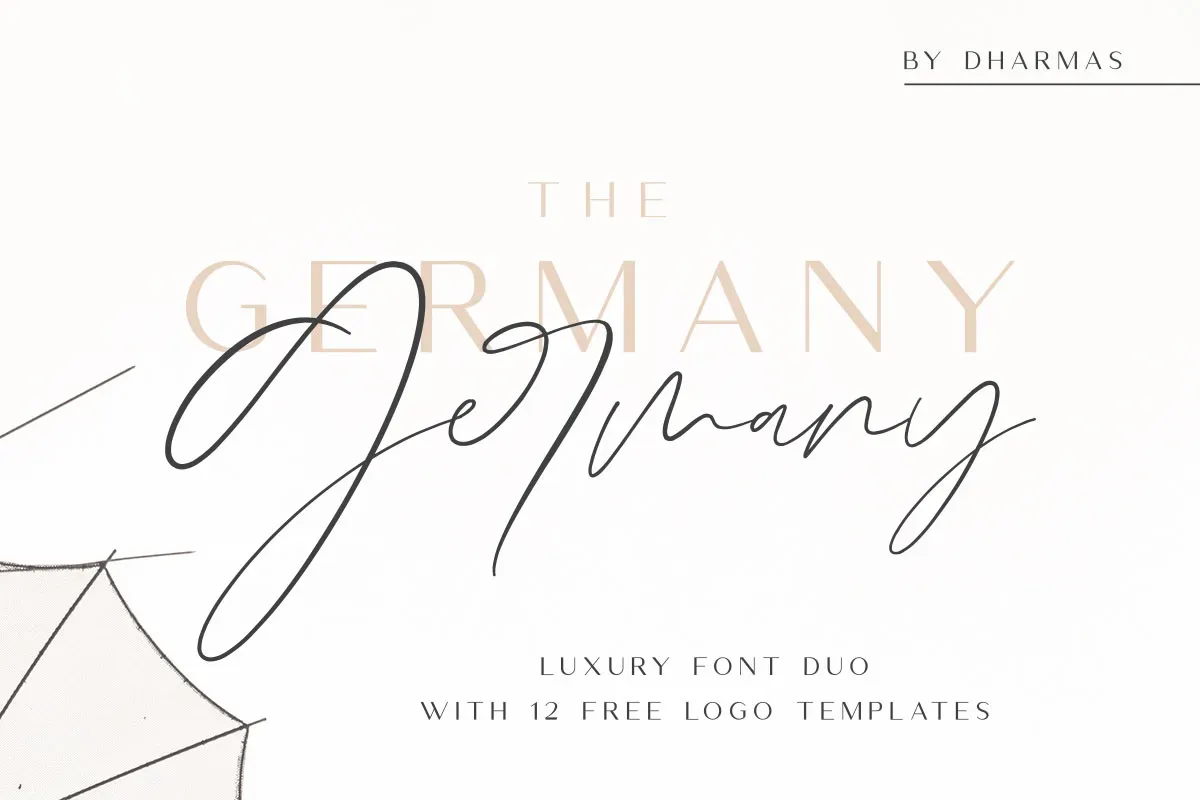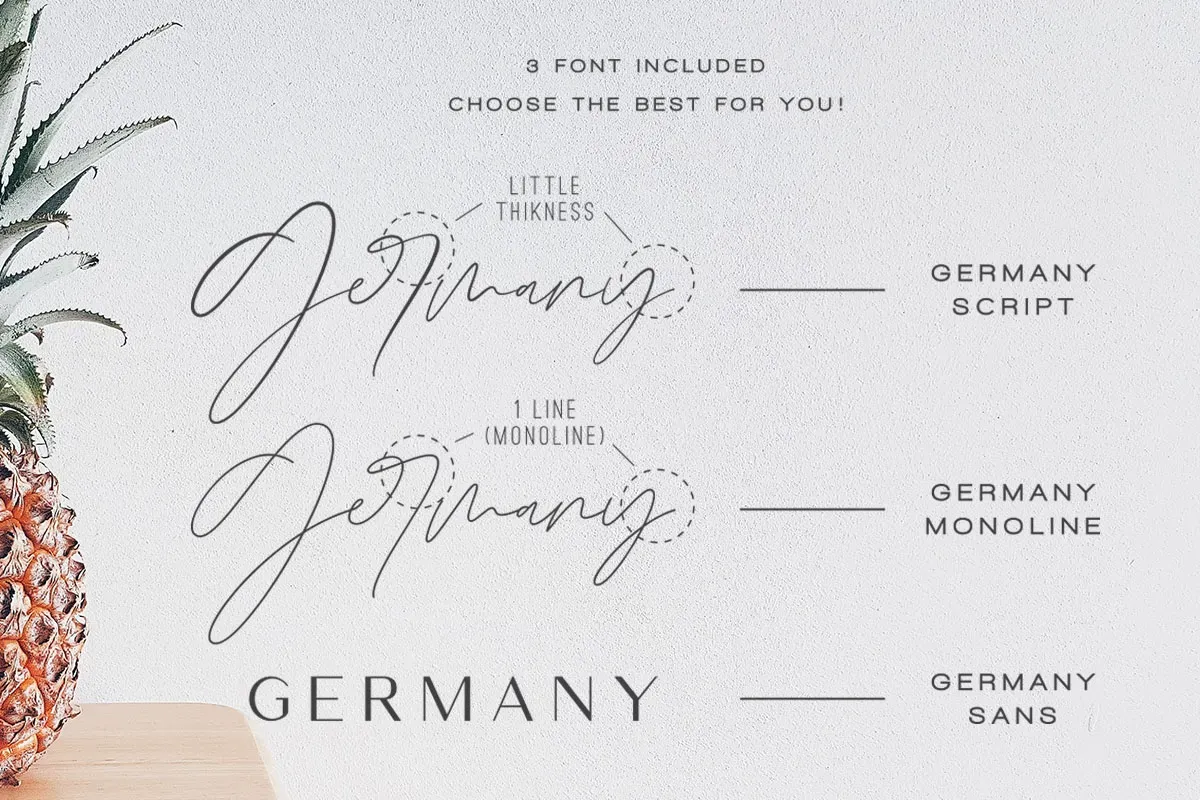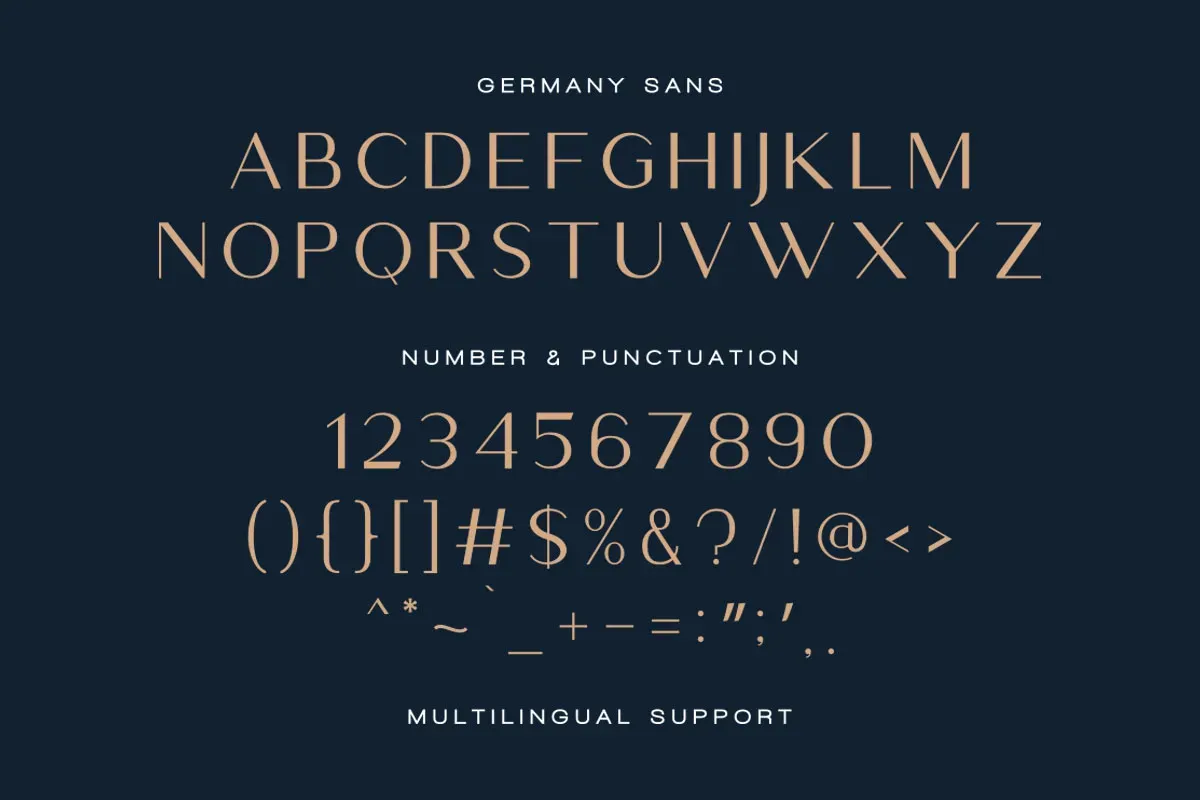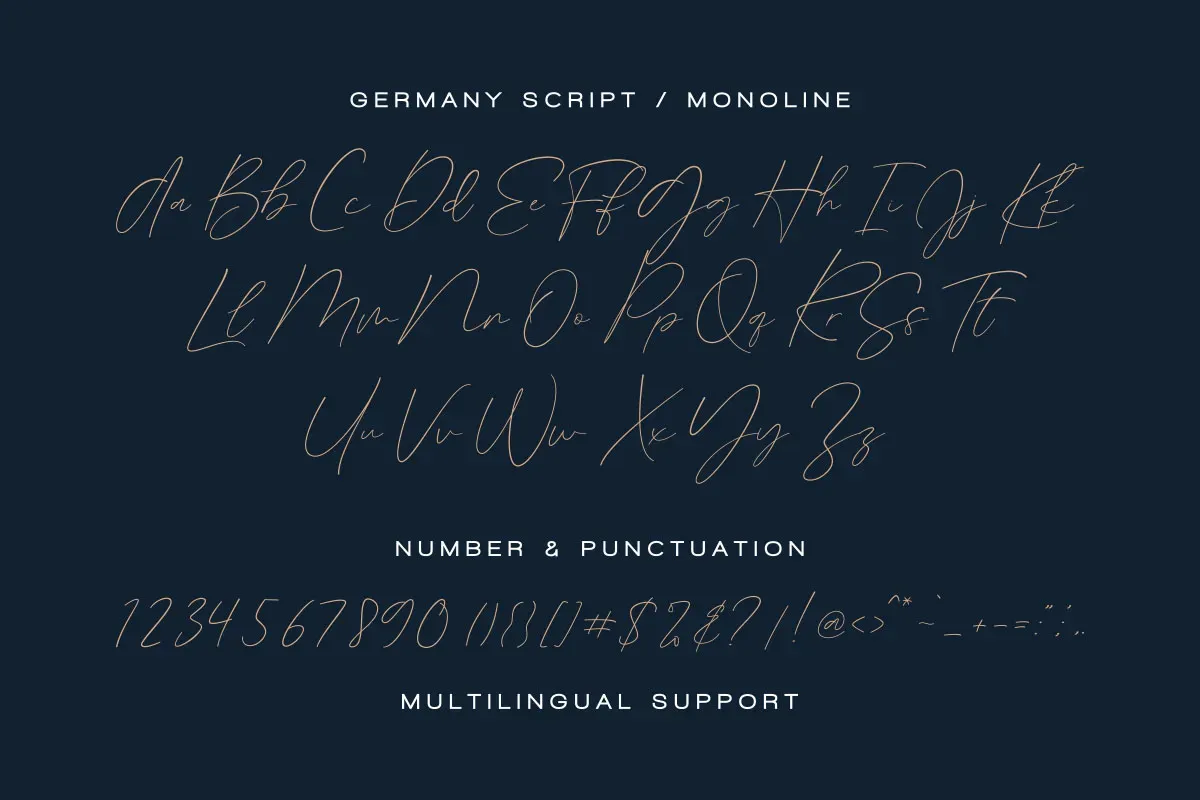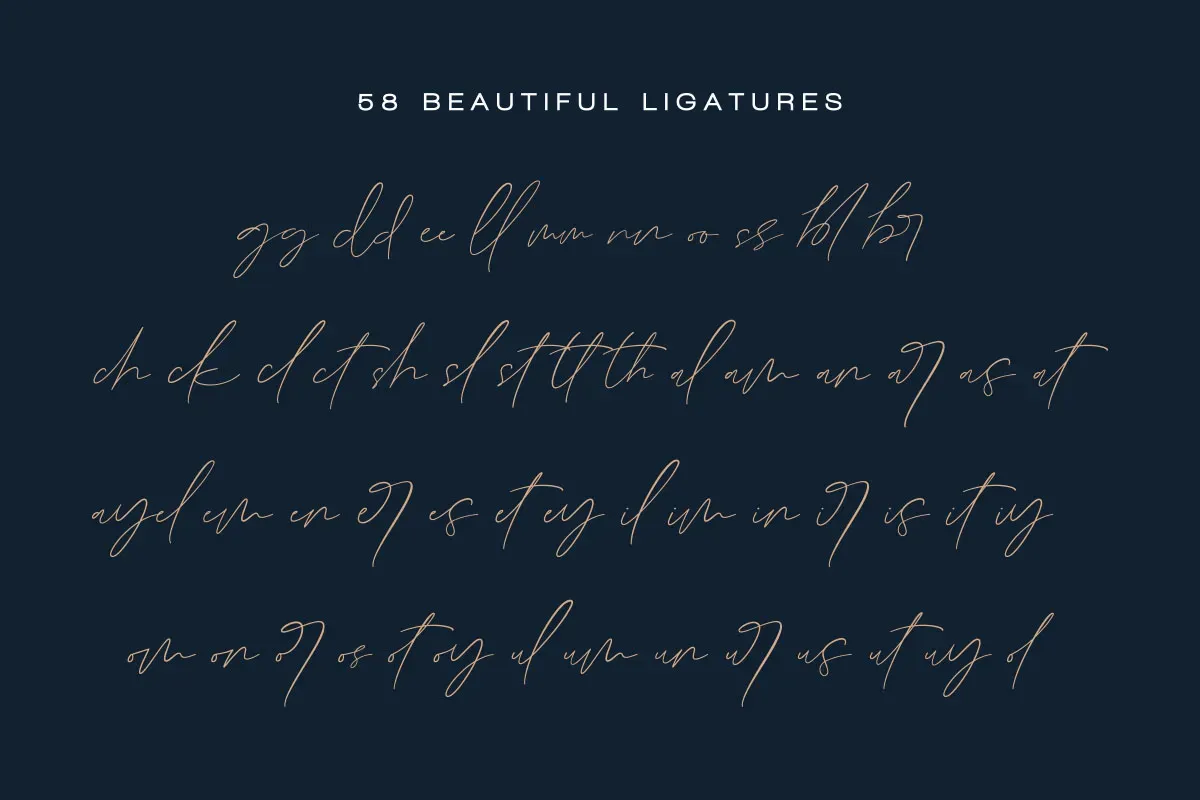
Germany Signature Script Font
Germany Signature Script Font é uma fonte duo luxuosa, composta por um elegante par de fontes script e sans serif. Combinando modernidade e sofisticação, ela é perfeita para projetos que buscam estilo e harmonia tipográfica.
Aplicações Perfeitas:
• Logotipos e Branding
• Convites de Casamento e Design Social
• Postagens para Redes Sociais
• Anúncios e Embalagens de Produtos
O equilíbrio entre a fonte script fluída e a sans serif sofisticada proporciona um visual de destaque, trazendo modernidade e classe aos seus projetos.